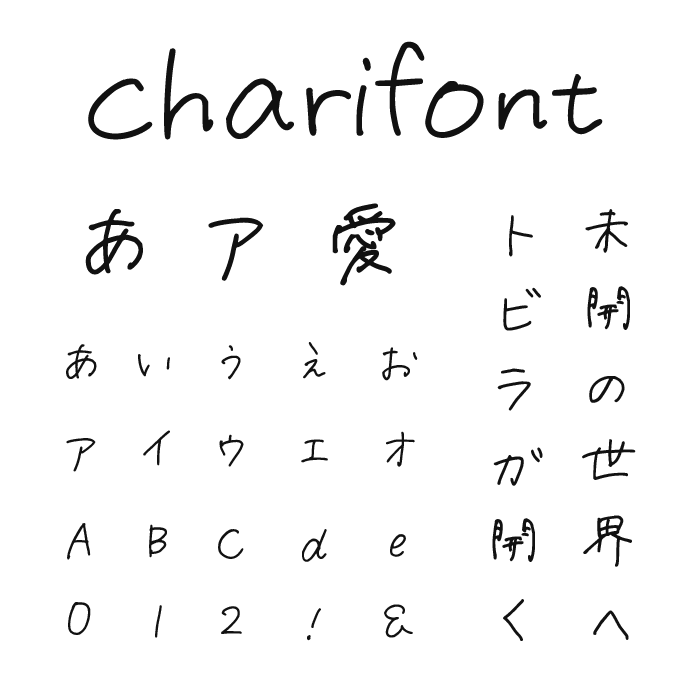
charifontは、やわらかく手書きの風合いを残した、ナチュラルで優しい印象の手書きフォントです。
かすれや揺らぎが程よく取り入れられ、リアルな手書きの風合いがとっても可愛らしい手書きフォントとなっています。
日常的であたたかみのある文章にぴったりで、エッセイのタイトルや雑貨のラベル、女性向けのパッケージデザインにもフィットします。素朴で癒しのある手書き感が魅力的なフォントです。
収録文字は、漢字・ひらがな・カタカナ・アルファベット・数字・記号が収録。